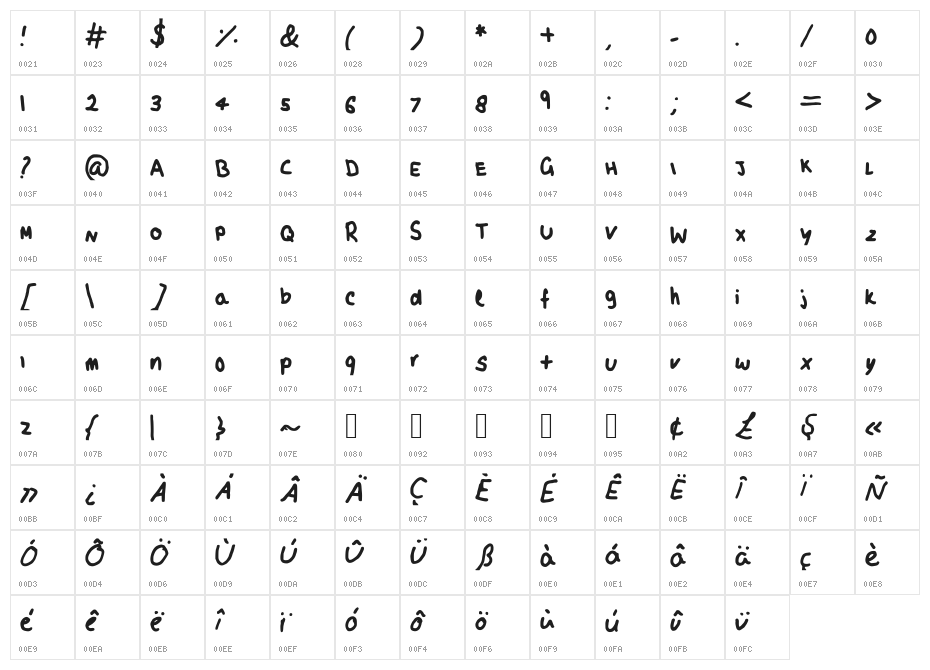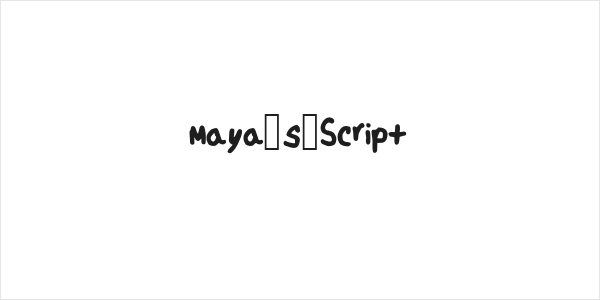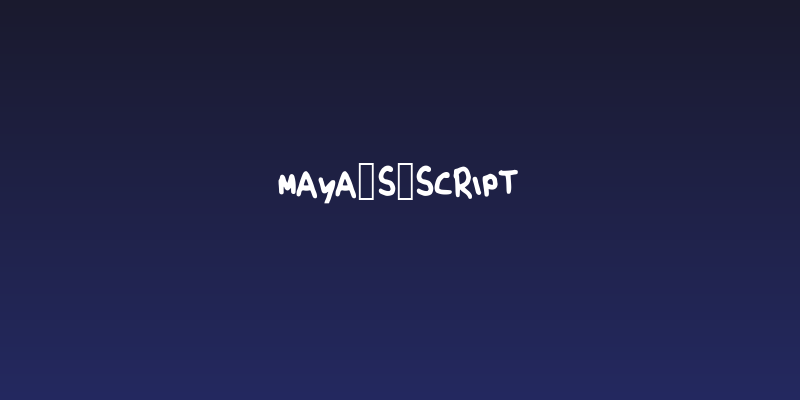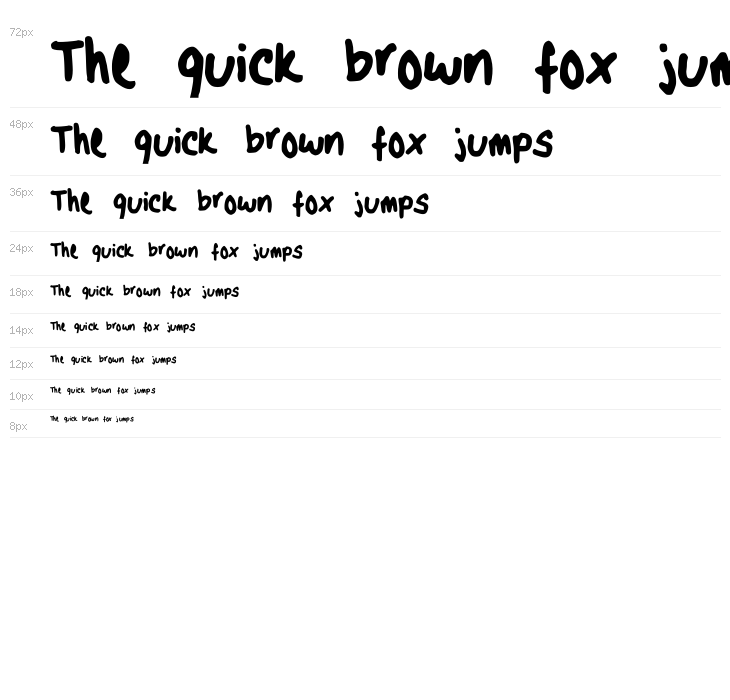
Maya_s_Script Font
| Stile generale | Casual |
| Caso d'uso | Logos, Headlines, Informal Text |
| Progetti proposti | Ideal for greeting cards, children's books, informal invitations, and playful branding projects. |